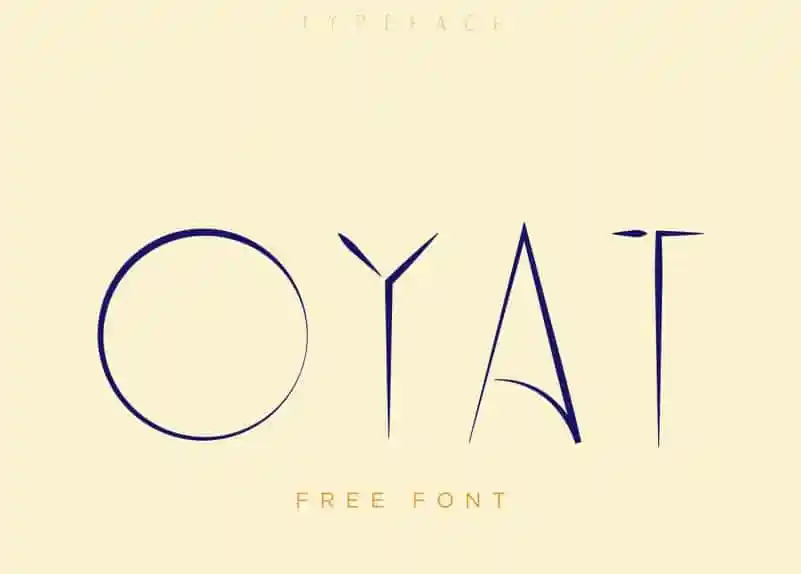
Oyat Display Font – Fonte Grátis
Oyat Display Font
Oyat Display Font é uma fonte serifada com um toque suave que adiciona uma leve curvatura a certos caracteres para ressaltar o valor femenino do desenho. Esta fonte foi criada e compartilhada por Johann Darcel Studio, e é perfeitamente adequada para projetos de marca, designs de casa, embalagens de produtos, cabeçalhos de revistas ou até mesmo como uma overlay de texto elegante em qualquer imagem de fundo. Suas linhas sutis e a curvatura suave da fonte dão um toque feminino ao texto, tornando-o perfeito para trabalhos visuais que buscam equilibrar formas geométricas com nuances mais naturais. Ideal tanto para textos detalhados quanto para grandes cabeçalhos, essa fonte traz sofisticação e personalidade a qualquer projeto gráfico.